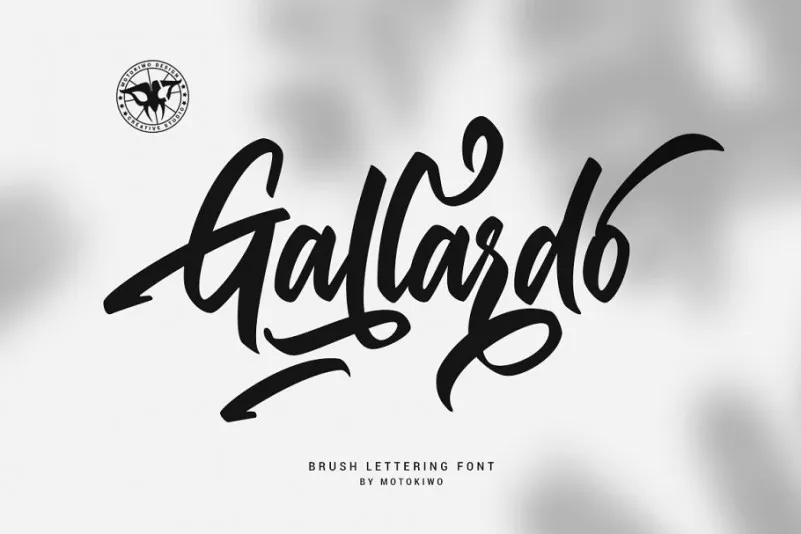
Gallardo Script Font – Fonte Grátis
Gallardo Script Font
Aqui está uma descrição para a página de download da font ‘Gallardo Script Font’, em português brasileiro, envolvente e natural: Nossa fonte Gallardo Script é um belo exemplo do gótico moderno, ideal tanto para projetos urbanos quanto vintage. Ela foi criada pela Motokiwo, com influências que misturam o passado com o futuro, resultando em uma escritura de alta qualidade e forte elegância. Se procura algo que combine a simplicidade e as linhas fortes do gótico moderno com um toque vintage, esta fonte é definitivamente para você. Ela traz um conjunto incrível de alternativas, garantindo que seja fácil encontrar o papel ideal para cada projeto. Ideal tanto para os designers urbanos quanto aqueles buscando algo vintage e sofisticado, a Gallardo Script vem vestida com influências do gótico moderno, fazendo-a uma opção irresistivelmente versátil. Com certeza, a fonte ‘Gallardo Script’ é uma ótima escolha para quem busca um estilo único no seu próximo projeto. Ela se adapta perfeitamente ao estilo de trabalho que você gosta e lhe oferece uma maneira única de fazer sua escritura brilhar. Instale-a em seu sistema, experimente algumas alternativas e veja por si mesmo como ela pode transformar seus projetos!